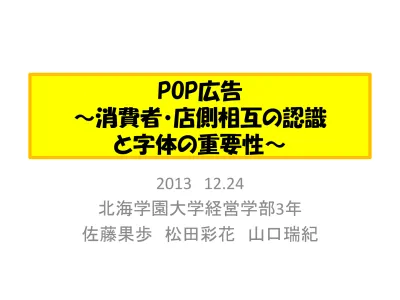
POP広告
~消費者・店側相互の認識
と字体の重要性~
第1章 研究目的
問い:セールスプロモーションは、本当に購買
意欲と関係していると言えるのか?
– 大量陳列
– サンプル、試供品 購買意欲の関係
– 値引き を調べるために・・・
第1章 研究目的
• 『セールスプロモーションの実際』
• 『売れる陳列売れない陳列』
• 『売り場づくりの知識』
POP広告が消費者に与える影響
POP広告によって購買意欲が高まる
消費者はPOPと認識して購買している
?
第2章 事前研究
方法
(1) 実際に店舗に行って調査
第2章 事前研究(1)
①アパレル(ex サマンサなど)
• 基本的なプライスカードなし
→値札はついている
• SALEなどのPOPは少しあり
第2章 事前研究(1)
②雑貨屋 (家具以外)
• プラザ
• ビレッジバンガード
• 無印良品
• ドンキホーテ
• LUSH
• フランフラン
第2章 事前研究(1)
商品そのものに
情報記載
自社の字体がある
商品一つ一つに
説明するPOP
基本的なプライスカード
分類
第2章 事前研究(1)
手書き風
印刷
情報量:多
情報量:少
雑貨の知覚マップ
第2章 事前研究(2)
紙=広告媒体
商品名
価格
キャッチコピー
説明文
イラスト
手書き
既存の
表示機材
第2章 事前研究(2)
<目的>
• 口頭説明の補助
勧誘・口頭説明 = 不快感になりうる
POP = 強制的でない
• 店頭イメージの訴求
売り場の雰囲気を一変させる!
第2章 事前研究(2)
<POP作成のポイント>
• 販売のねらい
• 商品の知識
• 貼り付け方法
• 大きさや形
• 書体や色
• 費用や素材
第2章 事前研究(2)
文字の種類でイメージ変化
• 安さ感を伝えるPOP
– ポップ体
– 丸ゴシック体
• 高級感を伝えるPOP
– 行書体
– 明朝体
– プレゼンス体
• 親近感を伝えるPOP
– クラフト体
– 丸ゴシック体
• 信頼感を伝えるPOP
– 華
– 平成ゴシック体
– 楷書体
第2章 事前研究 まとめ
<調査を通して疑問点>
• 店員はPOP広告を知らない?
• ビレッジ・ヴァンガードの店員は、POP広告と認識
して書いていない?
• ⇒(アルバイトもPOPを書くため)
• ×販促ツール
• ○店内の飾り
• 字体が消費者に与える影響は?
第3章 仮説1
POP広告の
第2章 事前研究 まとめから
<調査を通して疑問点>
• 店員はPOP広告を知らない?
• ビレッジ・ヴァンガードの店員は、POP広告と
認識して書いていない?
• ⇒(アルバイトもPOPを書くため)
• ×販促ツール
• ○店内の飾り
第3章 仮説1
商品の知識
知りたがっ
ていること
顧客の好み
信頼
本当にこれは守られて
いるのか??
第3章 仮説1設定
• 店側 ⇒ 以上のことを踏まえていれば
POPをPOPと認識していることになる
認識には違いがある!
第3章 仮説2
字体は消費者の
第3章 仮説2
POP
POP広告によって
購買意欲が高まる
第2章 事前研究 まとめから
店舗での検証から
⇒店舗によるPOPの違い =
字体
字体によって
買いたい
と思うよう
になるのか?
第3章 仮説2
• パッと見で目に入りやすい字体と
買いたいと思う字体は同じである
第4章 研究方法 仮説1
店員はPOPを知らない?
×販促ツール
○店内の飾り
この疑問に対し→
・アルバイト先にインタビュー
・論文で検証
第4章 研究方法 仮説2
アンケート調査
POPにする商品
• アヒル
• 電卓
• 10代から50代までの男女にアンケートを実施
・広告露出が少ない
・相場がわからない
・「欲しい!」となるよ
うなものでないもの
第5章 分析結果 仮説1
(先行研究)
• 購買計画の有無:対象入り場における商品の購買
計画を予め立てていたか消費者に尋ねる
• POP広告の有無:イメージ型POPのみ、両方を同時
掲出、価格型POPのみ、POP広告を掲出せずの順
に調査(合計4日)
*購買計画の有無とPOP広告の掲出状況が売り場内消費者行動に及ぼす効果
ーイメージ訴求型POPと価格訴求型POPを用いた現場検証
(牧野圭子、高木修、林英夫 著)
第5章 分析結果 仮説1
• あるスーパーの魚売り場
二日目
サーモン300円
ブリ 350円
価格訴求型
POPのみを掲示
一日目
秋といえば
さんまの季節
イメージ訴求型
POPのみを掲示
三日目
秋といえば
さんまの季節
100円!
イメージ型POP
価格型POP掲示
四日目
何も掲
示しない
第5章 分析結果 仮説1
・中華 = あったかいもの…暖色 (オレンジ+茶色)
・難しい漢字は使わない。
⇒遠くから見ると漢字はつぶれて見えづら
い。
⇒あったかい雰囲気にするため。
POP(販促ツール)としての認識あり!
第5章 分析結果 仮説1
・店舗内のPOP=本社から郵送されてくるもの
⇒店長が自発的に置いているものではない!
※しかし、POPを使えば売上は伸びるため、
販促品としての認識はある
第5章 分析結果 仮説2
36 4 50 3 0 5 10 15 20 25 30 35 40 45 50 POP体 ゴシック体 手書き 明朝体
可愛い
集計4 15 6 68 0 10 20 30 40 50 60 70 POP体 ゴシック体 手書き 明朝体
高級
集計18 20 52 3 0 10 20 30 40 50 60 POP体 ゴシック体 手書き 明朝体
安そう
集計41 13 36 3 0 5 10 15 20 25 30 35 40 45 POP体 ゴシック体 手書き 明朝体
可愛い
集計12 19 3 59 0 10 20 30 40 50 60 POP体 ゴシック体 手書き 明朝体
高級そうなのは?
集計11 10 64 8 0 10 20 30 40 50 60 70 POP体 ゴシック体 手書き 明朝体